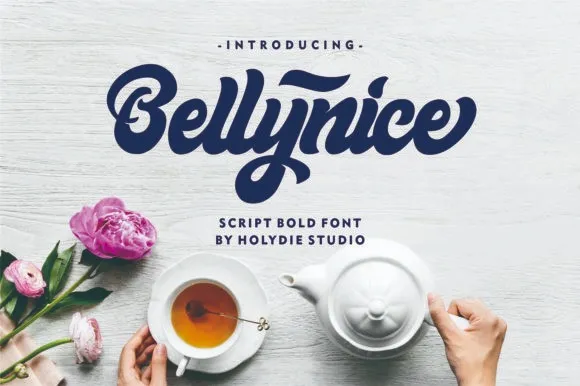
Bellynice Bold Script Font – Download Grátis
Olá amigos. Estou aqui uma fonte script bold que destaca-se do resto da multidão. Cada letra foi cuidadosamente trabalhada para tornar seu texto bonito e impecável. Introduzimos a fonte Bellynice. É um estilo de fonte script bold, inspirado em jelly fat. E é perfeito para adicionar uma aparência chamativa às suas criações. Esta font é adequada para Headlines, logomarcas, design tipográfico, desenhos de camisetas, convites, marca, embalagens, propaganda, design clássico e decoração de cartazes, entre outros. Não perca essa bela fonte. Ela vai revolucionar sua abordagem ao criar designs!